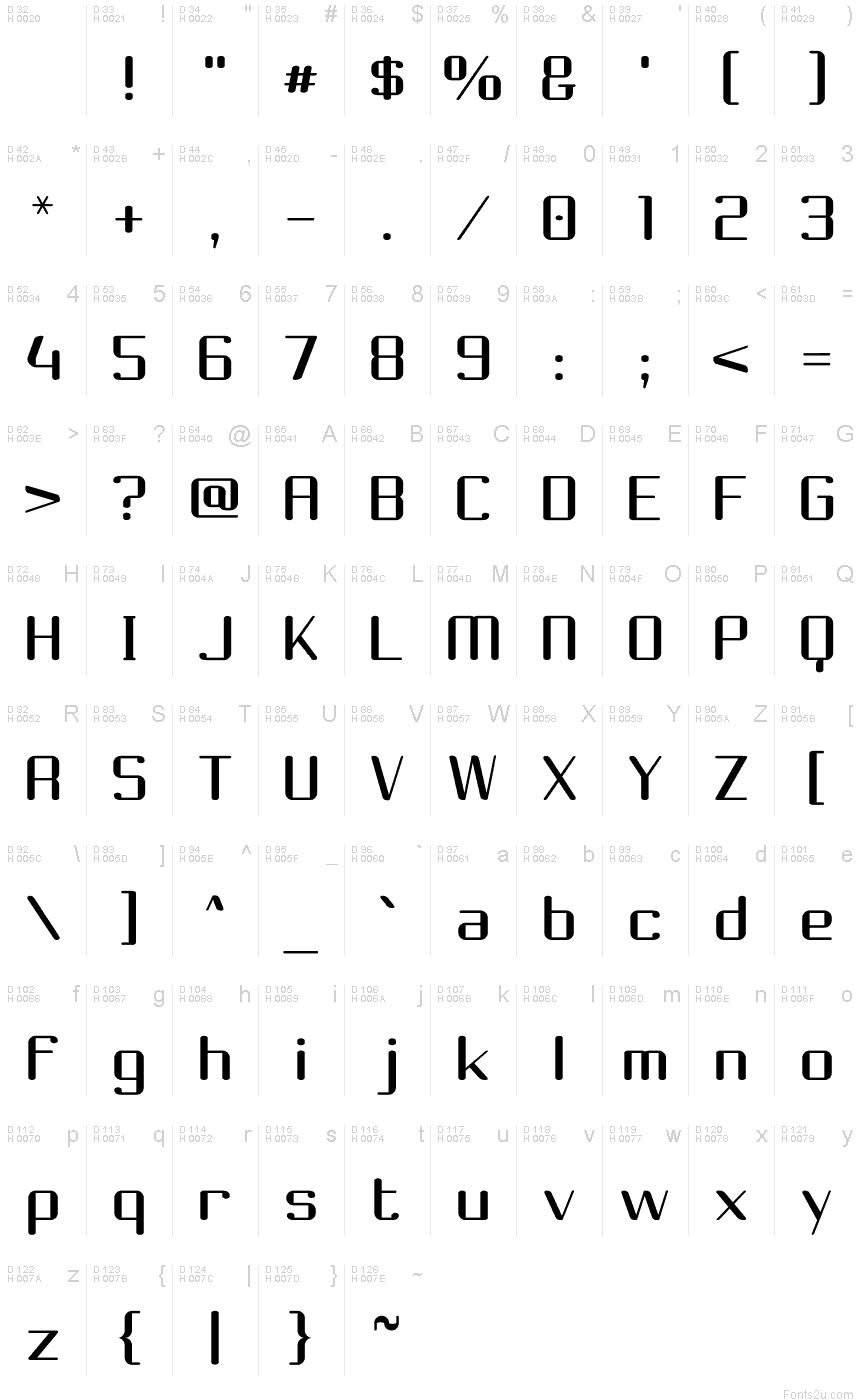
Choktoff هو خط لافت وعصري بامتياز، صممه جراهام ميد. بفضل أشكاله الجريئة والزوايا الحادة، وتصميمه الدرامي للحروف، يخطف هذا الخط الأنظار فوراً. جماليته الحادة التي تميل إلى المظهر الميكانيكي تجعله مثالياً لتطبيقات التصميم المعاصر، بدءاً من التصاميم التحريرية وصولاً إلى الهوية البصرية وواجهات الاستخدام الرقمية. السمات الفريدة وشخصية Choktoff المميزة تجعله الخيار الأمثل للمشاريع التي تبحث عن أثر طباعي قوي ومؤثر.
بفضل تعدد استخداماته، يتألق هذا الخط في العناوين والنصوص الأساسية على حد سواء، ليضفي لمسة بصرية قوية ومبتكرة في مختلف سياقات التصميم.